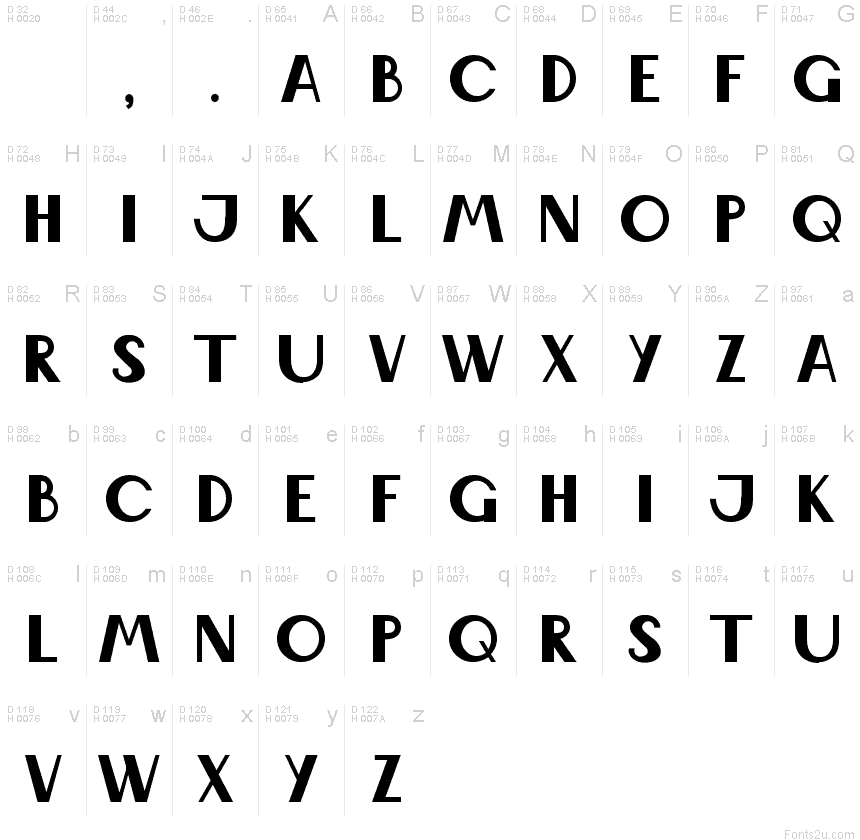
Wabene od Czcionki to darmowy, retro krój displayowy o oszczędnym, wczesnomodernistycznym charakterze. Litery są wysokie, wyraziste i geometryczne; ostre przekątne i zredukowane formy nadają wersalikom rytm typowy dla plakatu, daleki od nostalgicznej kaligrafii.
Sprawdza się tam, gdzie liczy się siła kilku wielkich słów – winiety magazynów, plansze tytułowe, okładki płyt, branding kawiarni czy opakowania w stylu vintage. Jako darmowy font, Wabene doskonale nadaje się do krótkich nagłówków, monogramów i napisów na okładkach, ponieważ jego kanciaste kształty i minimalizm sprawiają, że całość jest odważna, graficzna i ma w sobie ten niepowtarzalny klimat minionej epoki.
Wabene